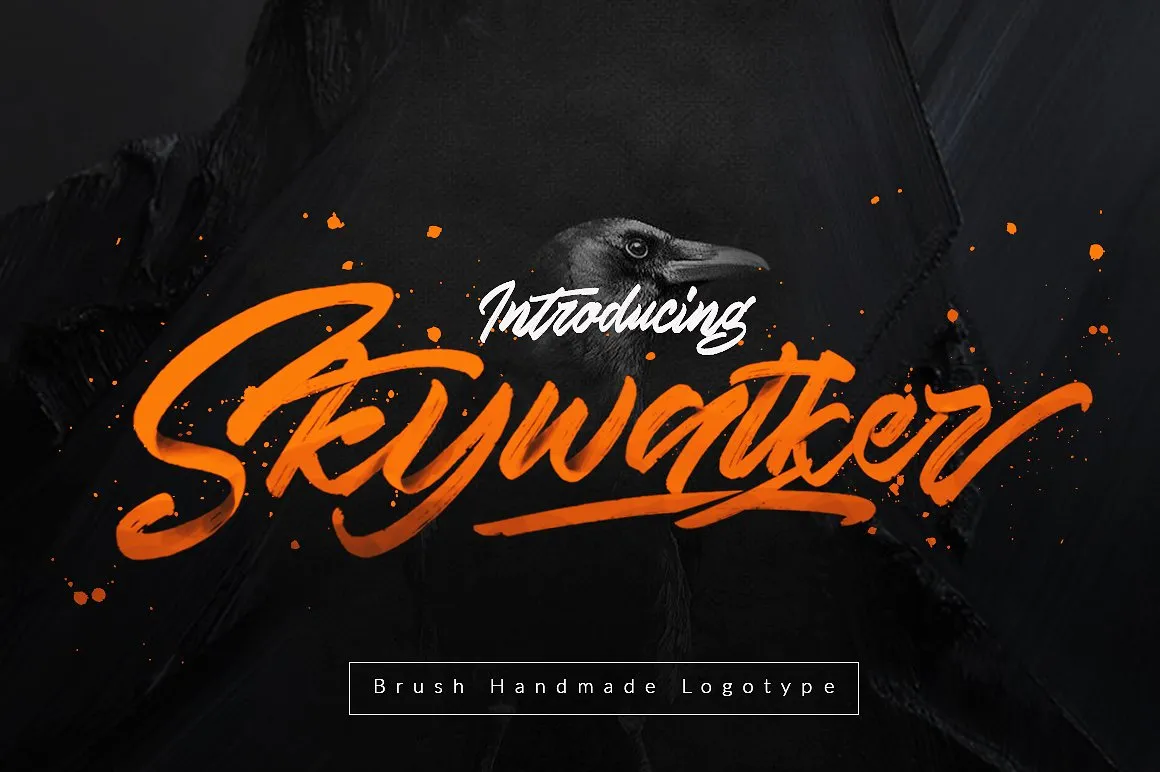
Skywalker Brush Font – Download Grátis
Introduzimos a nova fonte Brush Skywalker. Desenhada pelo Dirtyline Studio, esta fonte é ideal para uma ampla variedade de aplicativos, desde logotipos até cartões de cumprimentos e materiais de embalagem. A Skywalker apresenta um tipo cuidadosamente tostado, com imperfeições genuínas da tecnica de esfumar e uma base que oscila naturalmente. Ela também vem acompanhada de uma fonte complementar de marcador e um conjunto especial de swashes, tornando-a perfeitamente adaptável para as mais diversas necessidades de design. A sua qualidade perfeita permite que seja usada tanto em logotipos quanto em textos de citações manuscritas. Em termos de embalagens, o seu toque delicado e vibrante dá um toque único aos produtos, destacando-os de forma elegante e envolvente. Seja para criar cartazes ou materiais de mídia social, a Skywalker Brush oferece um resultado vibrante e moderno que se adapta perfeitamente às necessidades do seu projeto.